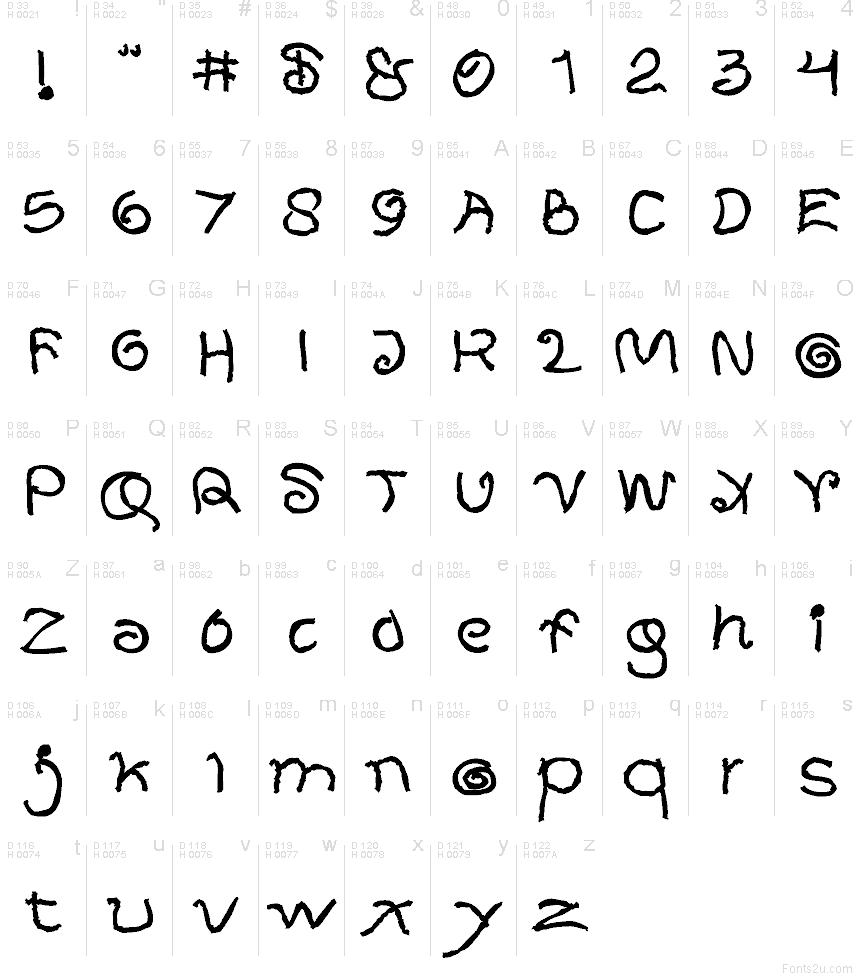
Fluid Story autorstwa Ffeeaarr to darmowy odręczny krój pisma displayowego z szerokimi pociągnięciami pędzla i surową sylwetką przypominającą wycinankę z papieru. Każda litera wygina się w swój własny kształt.
Małe studio artystyczne, niezależna wytwórnia lub eksperymentalna marka muzyczna mogłyby go użyć do opakowań i oznakowania, ponieważ nierówne krawędzie i nagłe zmiany pociągnięć sprawiają, że litery wyglądają na fizycznie wykonane, a nie wygładzone cyfrowo. Jego mieszanka wyrazistych śladów, otwartych krzywizn i ręcznie wycinanych nieregularności sprawdza się również w tytułach na plakatach, okładkach magazynów i gadżetach eventowych, gdzie krój pisma może bezpośrednio nawiązywać do malowanej grafiki lub kształtów kolażu.